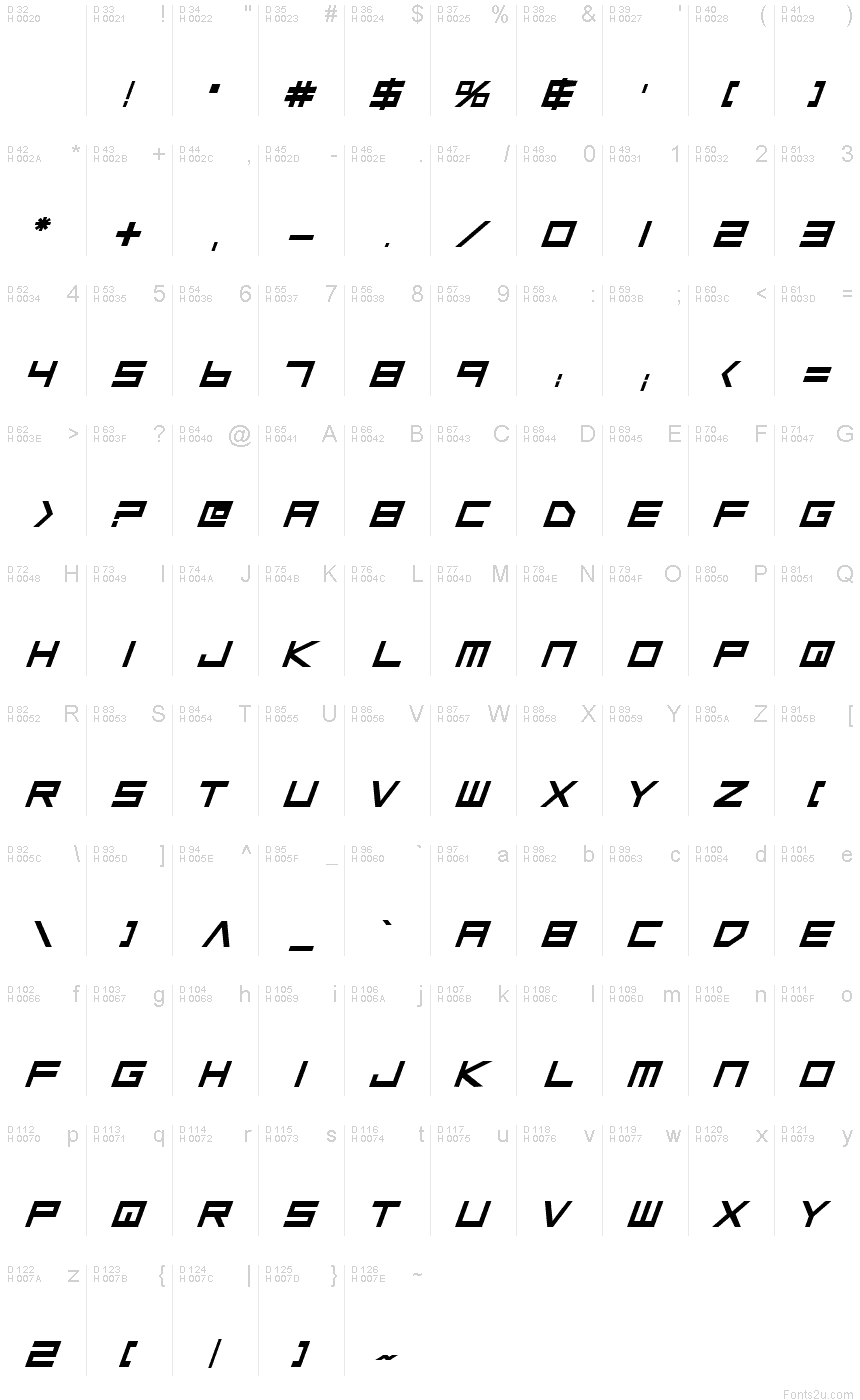
Low Gun Screen Bold Italic, un font display techno corsivo gratuito di Iconian Fonts, incanala la velocità tagliente della prima grafica digitale. Disegnato nel 2007, le sue maiuscole energiche si inclinano in avanti con diagonali affilate, aperture quadrate e tagli paralleli ripetuti che rendono il lettering veloce e tecnico.
Questo font gratuito è perfetto per loghi esports, poster di fantascienza, grafiche da corsa, titoli di videogiochi, copertine di album e banner per eventi. Funziona particolarmente bene per titoli brevi e testi di copertina, dove il ritmo inclinato e le forme tagliate hanno abbastanza spazio per sprigionare il loro impatto.